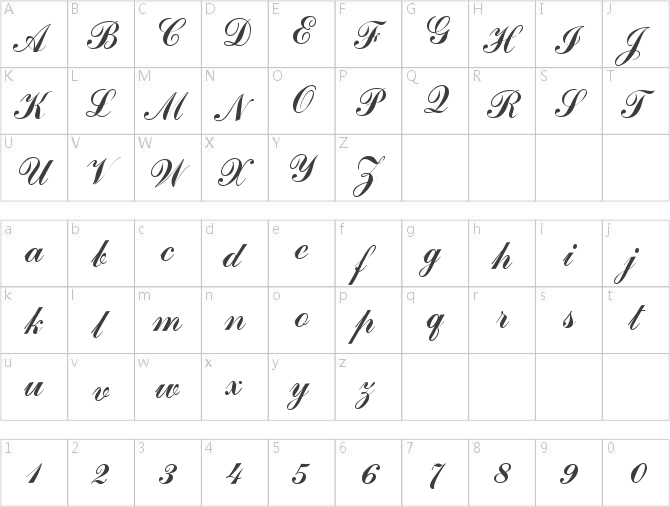
CommercialScript-Regular
CommercialScript-Regular介绍
CommercialScript-Regular字体字库是一款让人赏心悦目、百看不厌的英文字体,适合各类广告和产品包装设计应用,字体大小0.08MB,格式为ttf字体,上传用户是浪遍塞纳河的,作者/版权方为未知